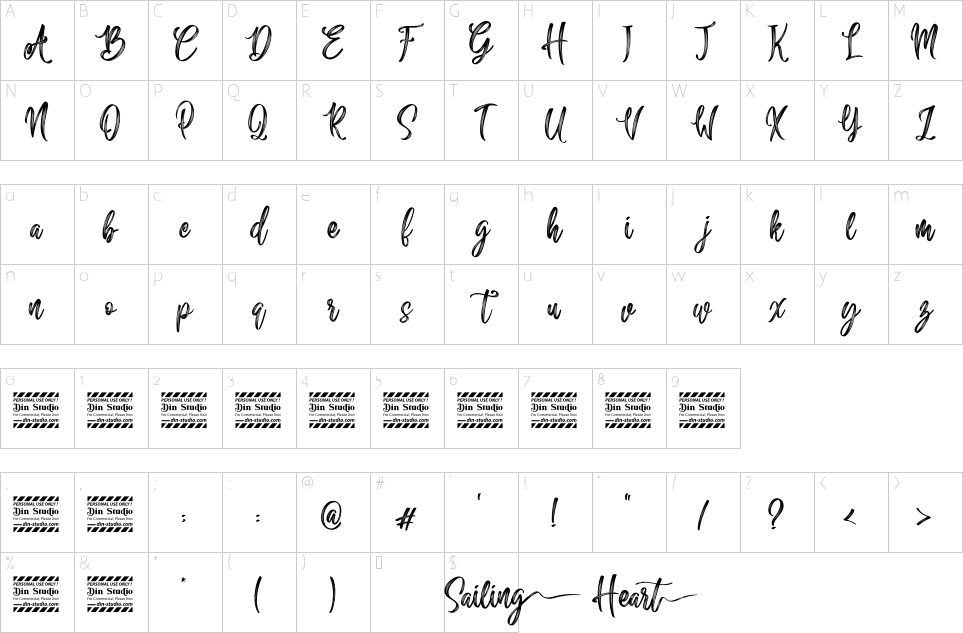
Sailing Heart é uma fonte elegante e minimalista que traz leveza e equilíbrio para qualquer projeto gráfico. Desenvolvida pelo Din Studio, a font é ideal para adicionar um toque de serenidade e harmonia a qualquer layout, seja em aplicações Windows ou Mac. Com seu design cuidadosamente pensado, a Sailing Heart combina perfeitamente com o estilo de vida tranquilo e despretensioso do brasileiro, que valoriza a simplicidade e a beleza dos movimentos naturais. Embora seu design não seja extremamente expressivo, a Sailing Heart é uma escolha perfeita para aqueles que buscam fontes suaves e sofisticadas para trabalhos que exigem um certo nível de calma e presença de espírito. Com sua simplicidade e beleza, a font Sailing Heart é uma excelente escolha para designers em busca de fontes gratuitas que se destacam em uma categoria cada vez mais competitiva de fontes gráficas.